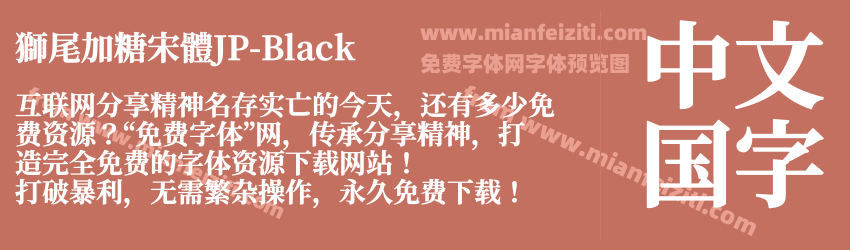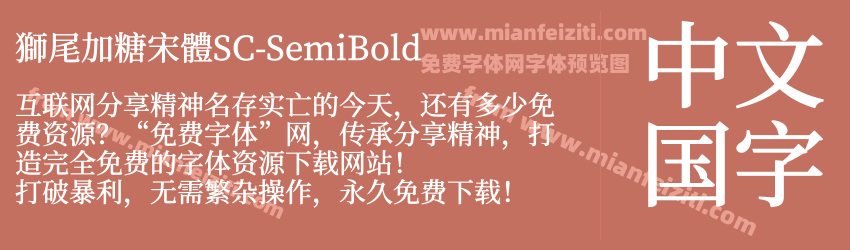
狮尾加糖宋体:给思源宋体加点糖 横笔加粗改造 免费商用字体资讯
狮尾加糖宋体是台湾友人Max发布的基于思源宋体的横笔进行加粗改造字体。和思源宋体的不同之处,思源宋体的横笔较细,狮尾加糖宋体是对字体进行了加粗处理,使宋体字形看上去更和谐。
狮尾加糖宋体和@新愚公发布的新愚公和谐宋思路基本一致,但是在实际效果上略有差异。新愚公和谐宋笔画会更粗一点,而狮尾加糖宋体看上去会更精致一点。大家可以按自己的喜好进行选择下载。
獅尾加糖宋體SC-SemiBold字体预览
獅尾加糖宋體JP-Regular字体预览獅尾加糖宋體JP-Black字体预览